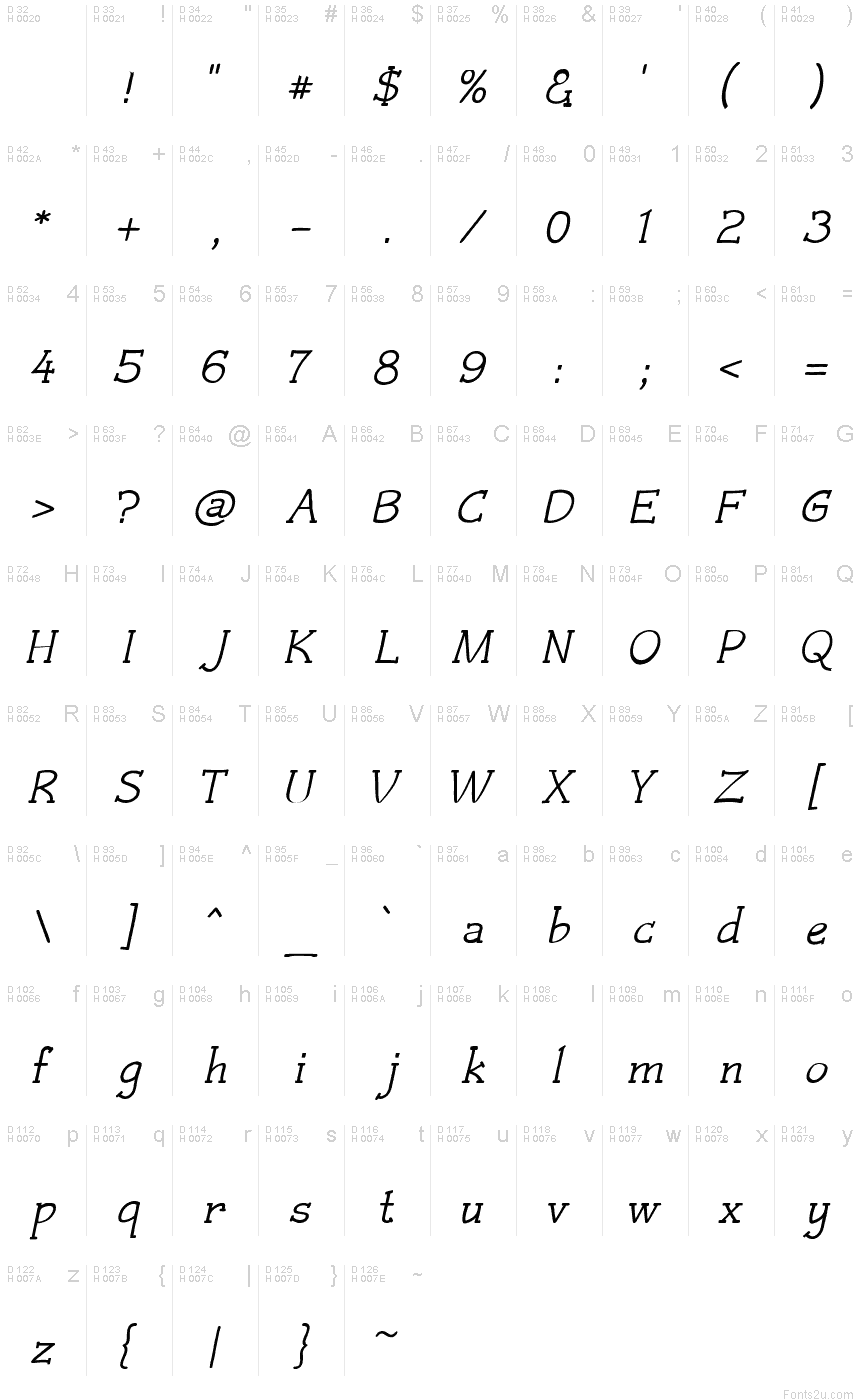
Czaristite Bold Oblique
Czaristite Bold Oblique autorstwa Grahama Meade’a to bezpłatny, odręczny krój pisma z rodziny Czaristite. Wyróżnia go szybkie, przypominające pismo tuszem na papierze nachylenie, które jest jednocześnie pewne siebie i nieco niepokorne. Pociągnięcia przypominają ślady pędzla, pozostają jednak w pełni kontrolowane, a pogrubiony krój zachowuje wyrazistość nawet przy mocnym pochyleniu w prawo.
Wykorzystując Czaristite Bold Oblique, nadasz natychmiastowej dynamiki okładkom książek, plakatom indie, okładkom albumów, menu kawiarnianym, cytatom redakcyjnym, znakom graficznym oraz wyrazistym nagłówkom w mediach społecznościowych. Ten bezpłatny font najlepiej prezentuje się, gdy ma dużo przestrzeni – wypróbuj go w dużym rozmiarze na prostych blokach kolorystycznych. Zestaw go z czystym krojem bezszeryfowym, takim jak Inter lub Helvetica, aby zachować energię bez wprowadzania niepotrzebnego zamieszania.